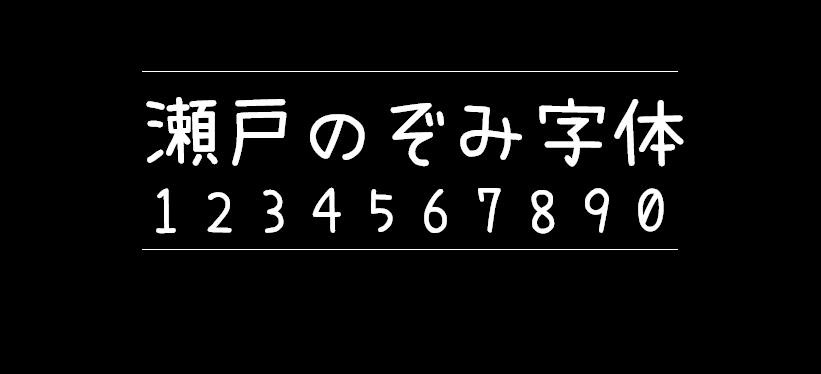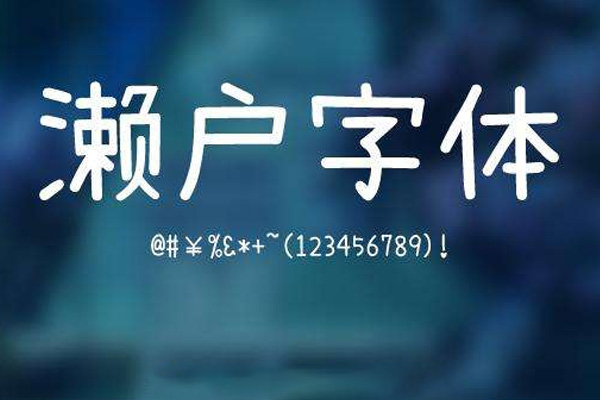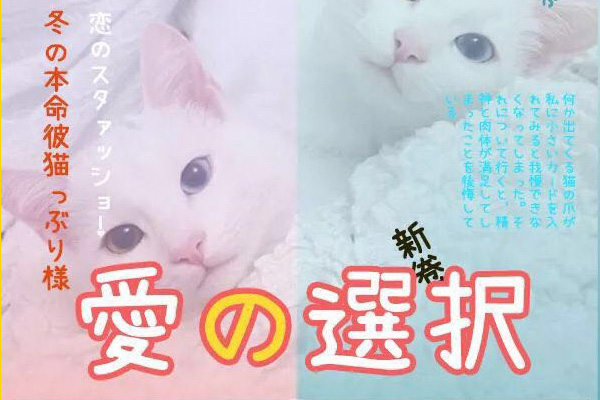
濑户字体介绍
濑户字型由日本的一位业余字体设计师 瀬戸のぞみ小姐 制作。支持简体、繁体、日文,而且支援日文包含 CJK 常用汉字、平片假名、JIS第一至四级,共 30000多字,是设计师个人手书,丝毫不造作,走的是一个好人缘天然呆的路线,甚至西文也很可爱。
濑户字体特点与风格‌
濑户字体设计者与起源‌:濑户字体由日本业余字体设计师(亦以主妇身份从事设计)‌濑户のぞみ(瀬戸のぞみ)‌ 个人手书创作,其笔触自然亲切,带有“好人缘天然呆”的独特气质。‌‌
‌濑户字体风格特点‌:字体整体呈现‌可爱、治愈系的卡通手写风格‌,笔画轻松随意,类似孩童笔迹,给人以认真呆萌的感觉。‌‌
‌濑户字体字形结构‌:字形‌修长舒展‌,重心略向上提升,搭配适中的中宫设计,显得灵动且平衡。‌‌
濑户字体笔画细节‌:笔画末端采用‌可爱圆头造型‌,圆角处理柔化了线条棱角,虽粗细均匀但透着纤细轻盈的质感。独特的‌笔画断开设计‌避免了连笔的繁复,让字符更显清爽利落。‌‌
濑户字体字符设计‌:西文字母(英文)设计也延续了俏皮风格,与中日文字符和谐统一。‌‌
濑户字体字符集与语言支持‌:字体覆盖‌CJK常用汉字、平片假名、JIS第一至四级字符‌,共包含‌超过30000个字符‌(亦有资料显示字符数达57620),全面支持‌简体中文、繁体中文、日文及英文‌。‌‌
濑户字体应用示例
濑户字体效果预览